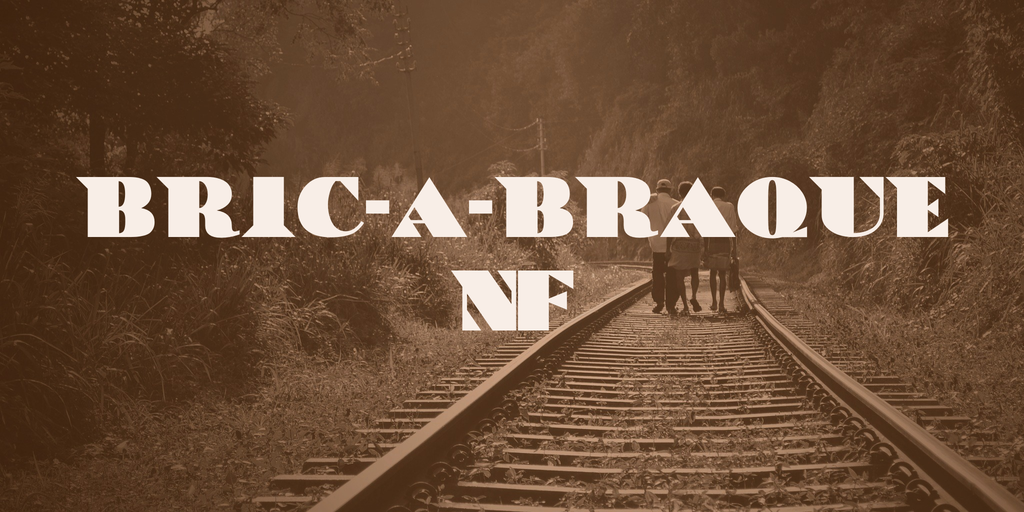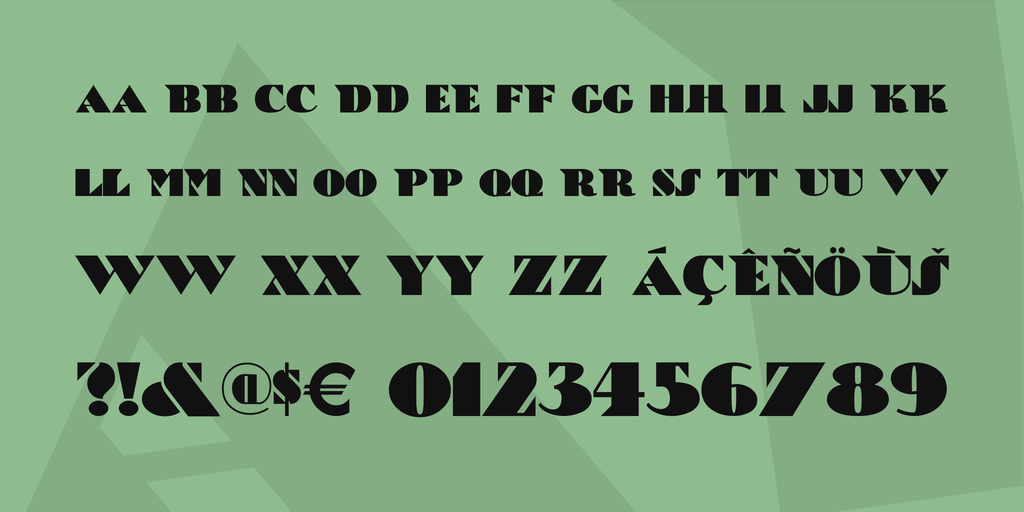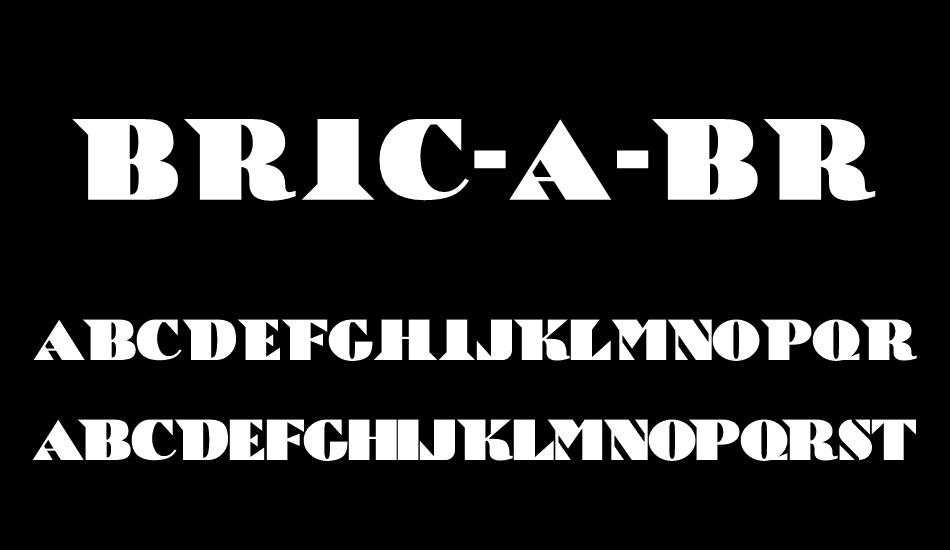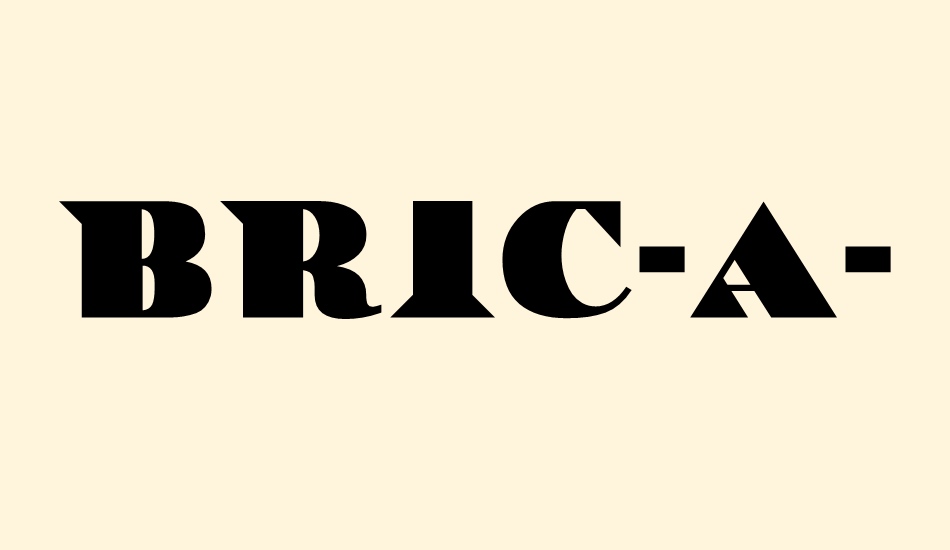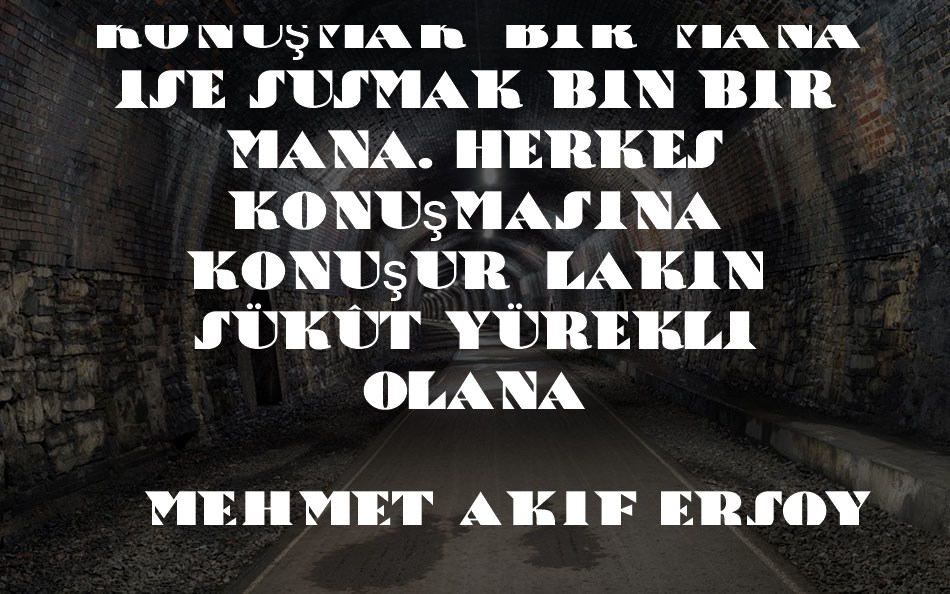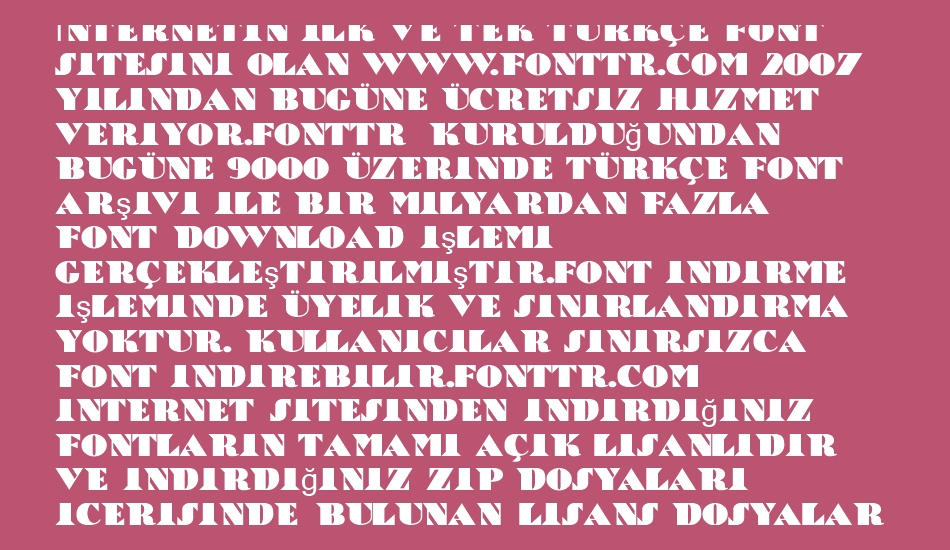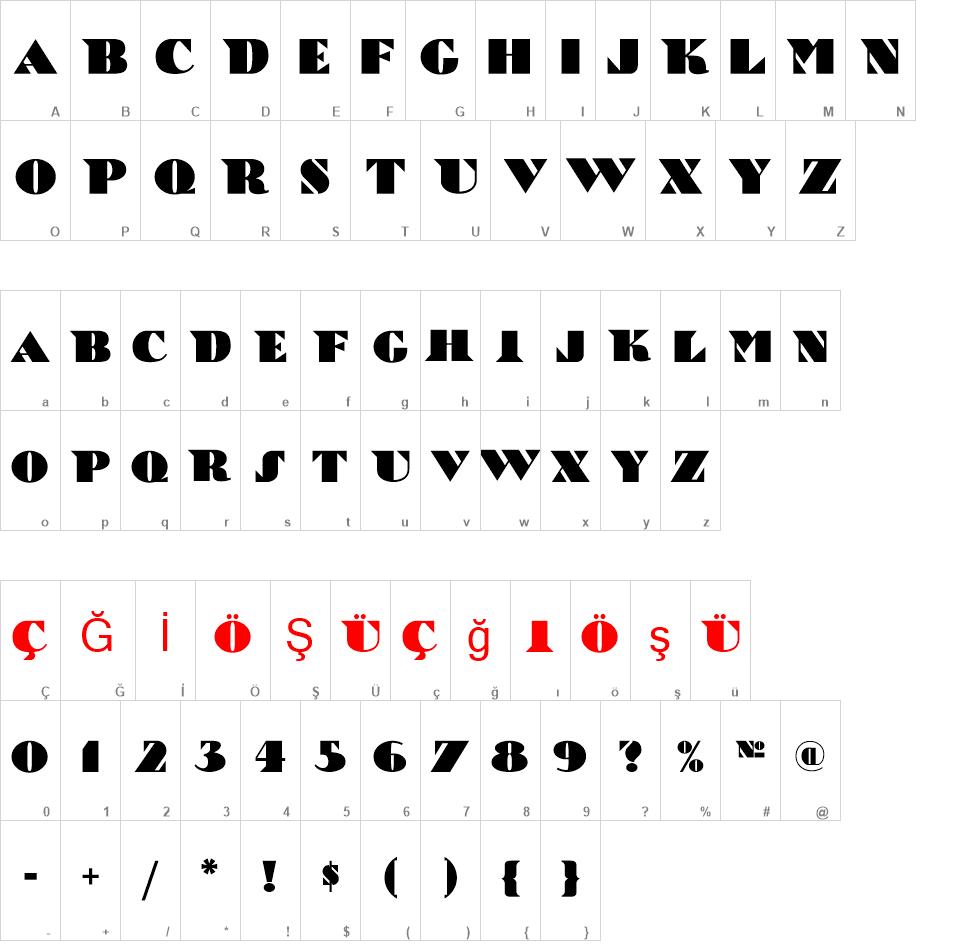
Bric
Die Autoren von Deco Type: Stilvolle Alphabete der 20er und 30er Jahre hielten dies zweifellos für die Quintessenz der Art-Deco-Schrift, weil sie sie auf dem Titelblatt ihres Buches verwendeten. Ursprünglich Cubist Bold genannt, wurde die Schrift von John Zimmerman für Barnhard Brothers und Spindler um 1929 entworfen. Meine Version kommt von einem Stück auf den Namen eines der Mitbegründer des Kubismus, Georges Braque (der andere war einige Typ namens Picasso).
Bric-a-Braque NF font